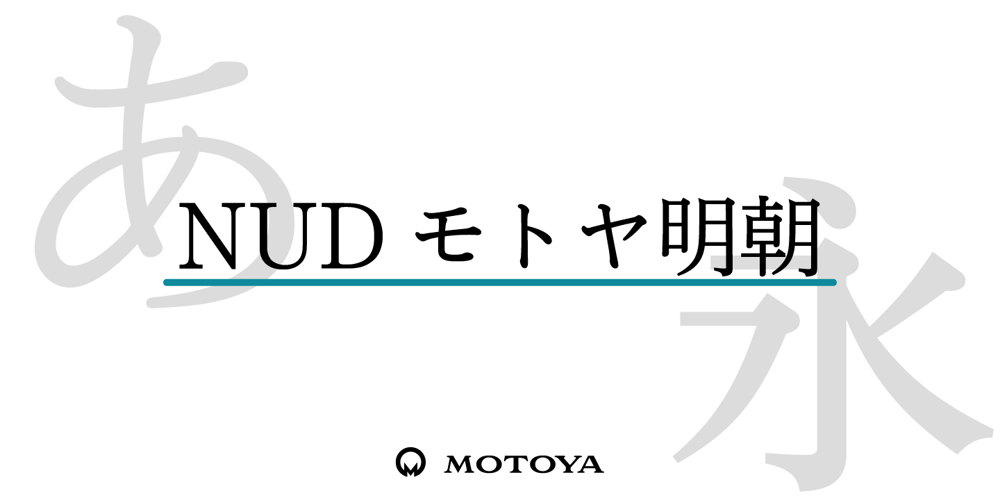
Nud Motoya Mincho Font Family was designed by published by Motoya. Nud Motoya Mincho contains 5 styles and family package options. モトヤ書体は活字時代から培った理念により、文字の美しさと優れた可読性を備えており、本来的にユニバーサルデザイン性を有しています。このように、もともとユニバーサルデザインを意識して開発を行ったモトヤフォントですが、社会状況の変化に伴って、より一層の改良を加えて誕生したのがモトヤUD対応フォントです。モトヤUD対応フォントは、可読性・視認性・判読性を併せ持っていますので、あらゆる分野のご使用に自信を持ってお勧めいたします。